网红奶茶品牌“喜茶”注册有“HEYTEA”系列商标,而一家咖啡公司随后注册了“HEY”图形商标(简称争议商标),核准使用在餐厅、咖啡馆等服务上。“喜茶”方认为该商标构成侵权,国家知识产权局经审查对争议商标宣告无效。咖啡公司不服,起诉至法院。
据悉,“喜茶”的经营方为深圳美西西餐饮管理有限公司(简称美西西公司),其自 2014 年起陆续注册了“HEYTEA”、“HEYCHA”等多枚商标,核定使用在餐厅、茶馆等服务上。
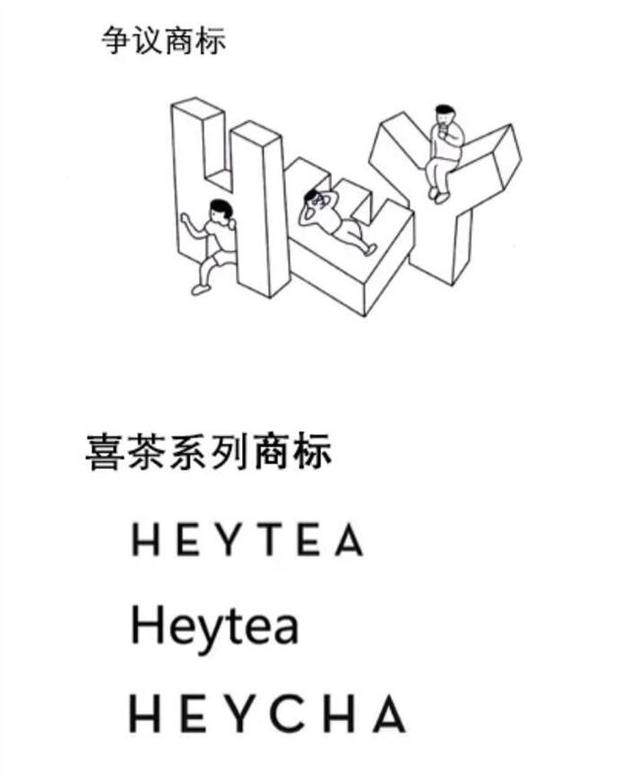
而 2017 年 7 月,广州创业咖啡有限公司(简称创业咖啡公司)申请注册了“HEY”图形商标,核准使用在餐厅、咖啡馆等服务上, 2018 年 7 月获准注册。这枚商标以字母“HEY”为主体,字母上绘有多个或坐或卧的人物。
国家知识产权局经审查认为,美西西公司没有提交有效证据证明其享有“HEYTEA”插画的在先著作权,但争议商标与“HEYTEA”系列商标在文字构成、呼叫及含义等方面相近,构成近似标识。由于争议商标与喜茶商标都核定使用在餐厅等服务上,属于相同或类似服务,容易使相关公众对服务来源产生混淆误认,应认定构成近似商标,于是对争议商标裁定予以无效宣告。
创业咖啡公司不服国知局裁定,起诉至北京知识产权法院。
创业咖啡公司表示,字母组合“HEY”只是争议商标的创作要素之一,且已经进行了艺术化的处理,与喜茶系列商标具有明显差异。这枚商标获准注册后,实际使用中,并没有发生损害他人合法权益或造成消费者混淆误认的情形,故请求法院判令国知局重作裁定。